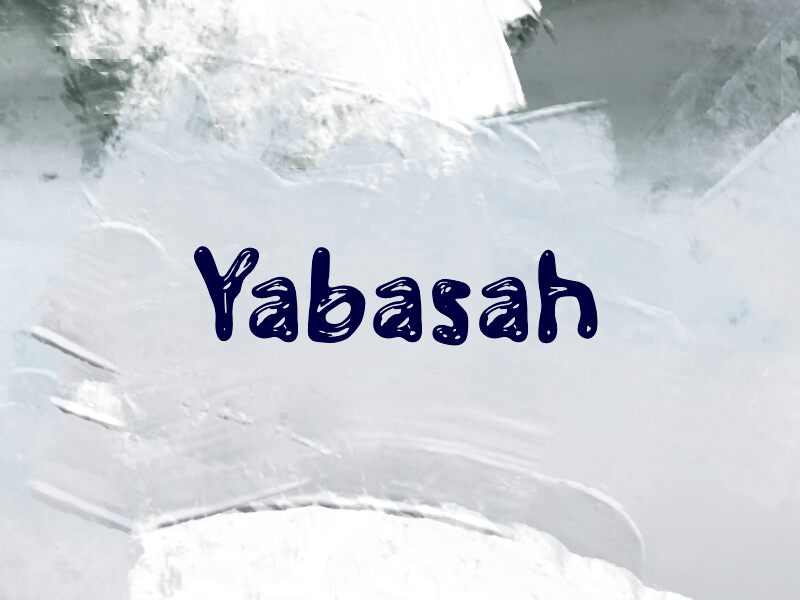
Yabasah
Yabasah od Wep je bezplatné display písmo v kresleném stylu, které vypadá jako z tlustých inkoustových písmen s jasnými zářezy a kluzkou, ručně tvarovanou siluetou. Zaoblené tvary se mírně vlní, což designu dodává komiksovou, gumovou texturu namísto strojeného stylu maskotů.
Tento lesklý "blob" efekt dodává krátkým titulkům výrazný charakter na dětských plakátech, obalech svačin, pozvánkách, miniaturách YouTube nebo hravé grafice. Díky vypouklým tvarům a efektu mokrého lesku skvěle vynikne i na nálepkách nebo příspěvcích na sociálních sítích, kde design unese vtip i bez dalších ilustrací.